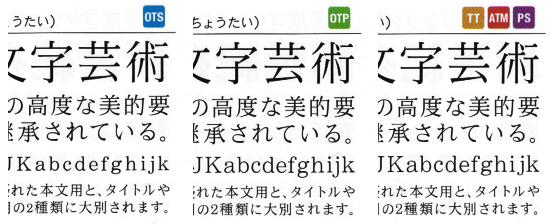
なんてことはない、「華康明朝体っぽい何か」は華康明朝体だった件
一昨日のエントリにこう書いた。
[…] あれは何の書体だろう。あの不揃い感。何度か書体見本と比べてみたところではダイナフォントの華康明朝体っぽいんだけど、「ま」の字形が違う。よくわからん。
で、改めて「DynaFont 総合カタログ 2008」を引っぱり出して見てみたところ、どうやら「華康明朝体っぽい何か」は華康明朝体そのものだったっらしい。ただし、改良前の。
次の画像は、このカタログの p. 3 からとったもの。華康明朝体W3。
左の OpenType Std 版と中央の OpenType Pro 版とを比べてみると、「さ」の1画目の終筆や「い」のふところの大きさ、そして「ま」の横画の長短などが異なっていることがわかる。アルファベットも全体的に変更されている。一方、右の TrueType / ATM-CID / PostScript 版では、中央の Pro 版と同じ字形になっている。
上の華康明朝体のリンク先では OpenType 版は,かなを中心に改良されている
と書かれていたが、どうやら「OpenType Std 版は改良前の字形のまま、OpenType Pro 版はじめ他のフォントフォーマットでは改良後の字形を収録」というのが現状の様子。
# 一迅社文庫は小塚明朝L、一迅社文庫アイリスは華康明朝体W3。
# 書体についてもう少し考え直してもいいような……。